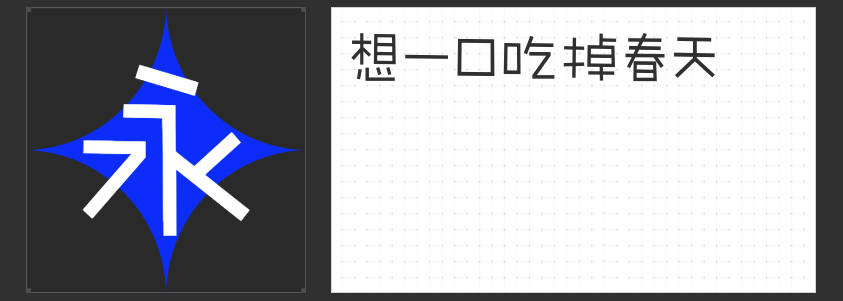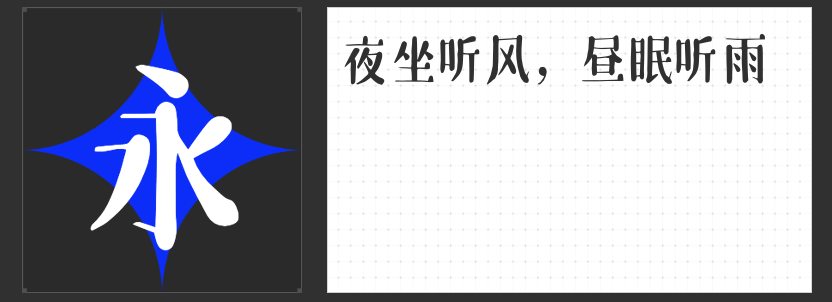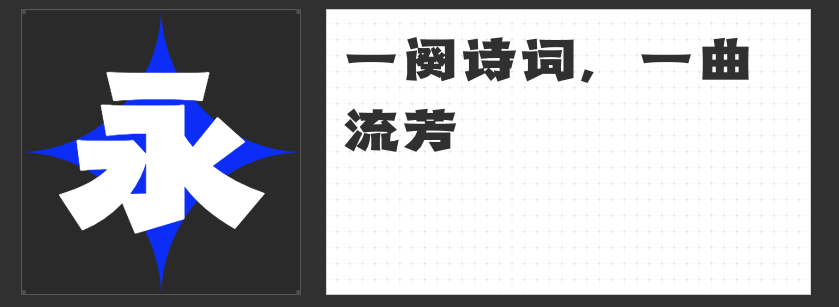
包装设计精选字体推荐:打造独特视觉体验
在包装设计中,字体不仅是传递信息的工具,更是展现品牌个性和产品特色的重要元素。今天,为大家推荐四款适合包装设计的字体,它们各具特色,能够为您的产品包装增添独特的视觉魅力。
这款字体略带俏皮,充满趣味与想象。其手写的圆润线条在保留辨识度的前提下,省略了部分笔画,呈现出简单明快的线条和独特的形式。这种用心书写的随性感觉,让字体更具手绘感,带来手写的柔软和温暖。非常适合用于儿童产品、甜品包装等充满趣味性的场合。
励字志向黑简 大粗采用圆体与黑体的融合,通过增加笔画拐角的外圆角手法,为整体稳重大气的字形增添了一丝灵动。这款字体字面充实,结构稳定,同时更适配屏显的使用。它适用于高端产品的包装设计,能够展现出产品的品质和品牌的稳重感。
这款字体以手写感为基础,整体圆润略瘦长,中宫适中,设计生动灵活。笔画保持了传统宋体横细竖粗的特点,同时笔形圆润,横笔画末端加入了圆形元素装饰角,钩笔画笔形细长圆润,略微上挑。这种设计让字体更具趣味性,适合用于文化产品包装、文艺类商品的包装设计等。
四、造字侠热辣隶简
造字侠热辣隶简结合了传统隶书特点与现代设计元素,整体结构稳定、中宫扁宽,具有较强视觉冲击力,给人庄重威严之感。其笔画线条简洁明快,撇捺起收笔细粗自然过渡,横笔开张对称,竖钩及弯钩的书写力量以直线高度概括。这种多样性的笔画既保留了历史感,又富有现代气息,适用于国潮设计、教育、文化产品包装、海报、品牌塑造等应用场景。
这四款字体各具特色,能够为您的产品包装增添独特的视觉魅力。在选择字体时,请根据您的产品特点和品牌调性进行挑选,以确保字体与整体设计的和谐统一。